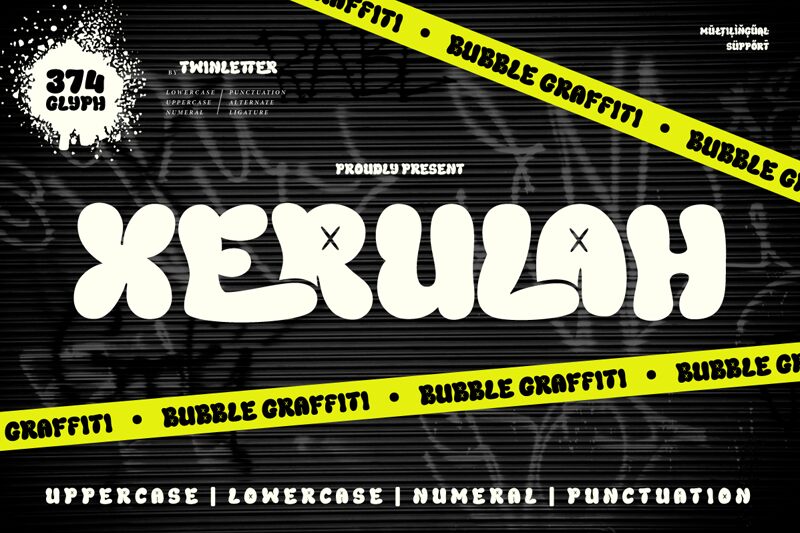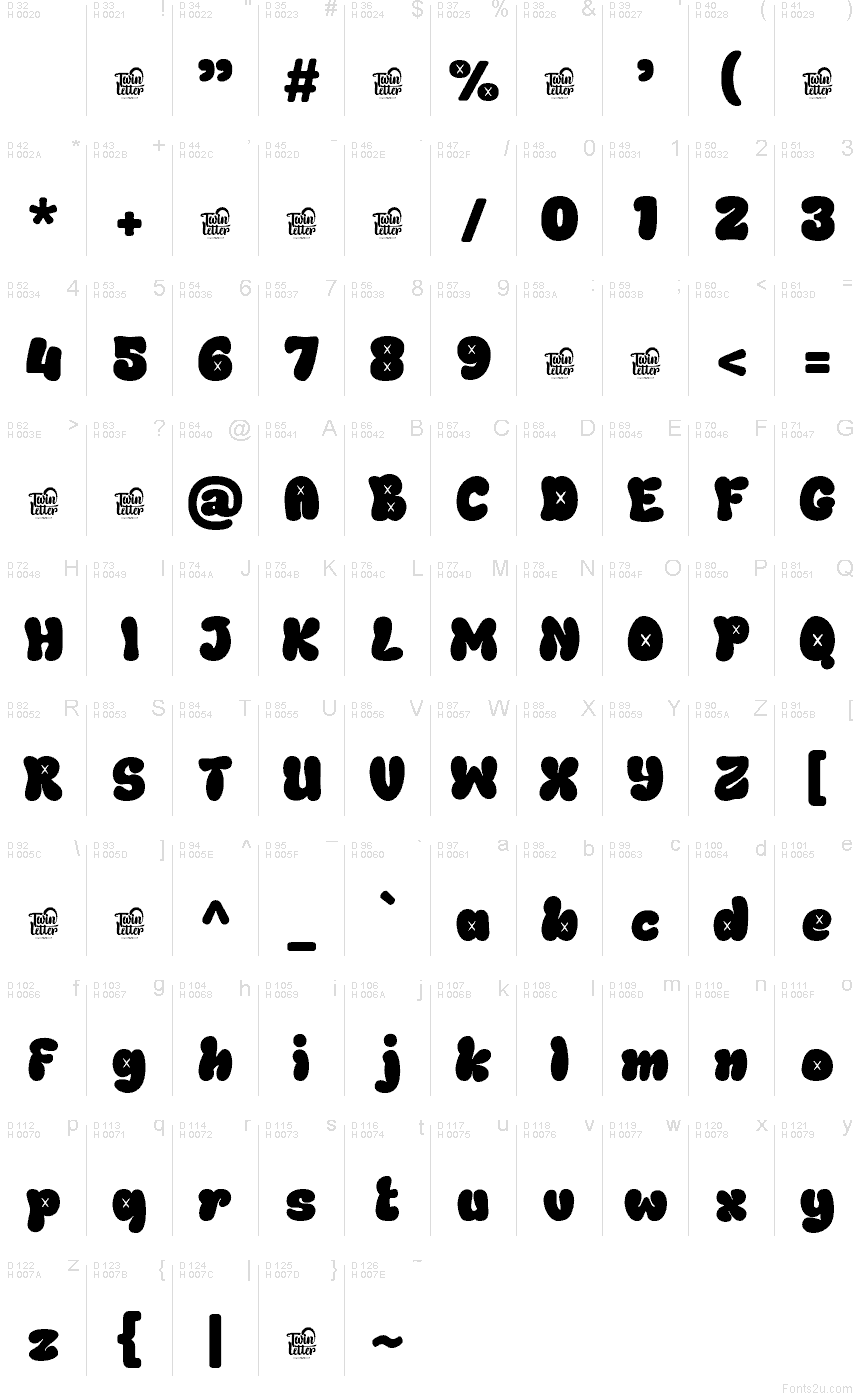
Xerulah di Twinletter è un font display gratuito in stile cartoon, caratterizzato da lettere sovradimensionate e morbidamente gonfie. Le curve irregolari, le giunzioni strette e i piccoli intagli a forma di croce donano alle scritte una silhouette vivace e gommosa.
Il packaging rappresenta una scelta ideale, in particolare per dolci, giocattoli o snack giocosi che traggono vantaggio da una tipografia con carattere da mascotte. Possiede inoltre l'incisività necessaria per manifesti per bambini e titoli animati. Adesivi e grafiche per eventi informali offrono un'ulteriore collocazione ideale per le sue forme rimbalzanti.